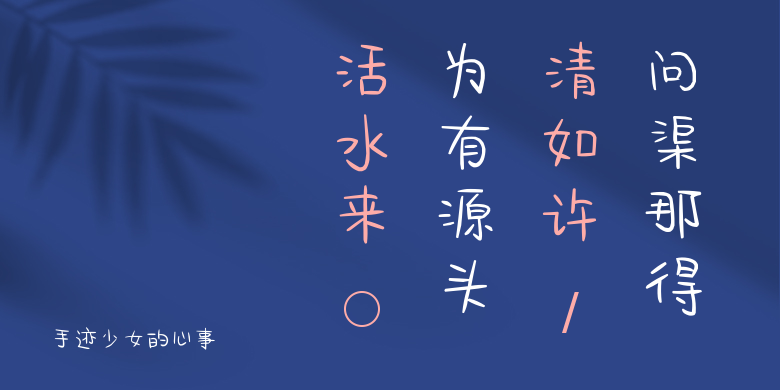
手迹少女的心事
手迹少女的心事,这款字体结构工整、笔画清晰,兼顾美观与易读性,适用于标题、正文、海报、包装、LOGO 等多种场景。字形优雅稳定,风格百搭耐看,适配日常排版与创意设计,让文字呈现更舒适、更具质感。手迹少女的心事一笔一画,皆是细节,以均衡的比例、流畅的线条打造舒适视觉体验,字形端正大气,风格简约现代。无论是商业设计、品牌宣传还是日常排版,都能轻松驾驭,让文字更有格调与力量。手迹少女的心事字体下载。